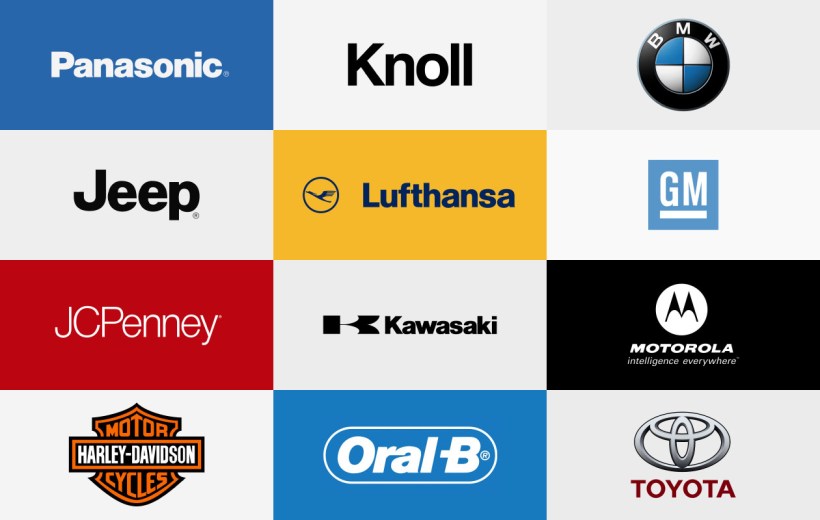
En ces jours de télétravail et de pause forcée à votre domicile en raison de l’urgence du Coronavirus, je vous propose de découvrir les documentaires du réalisateur Gary Hustwit qui a décidé de diffuser gratuitement ses films durant le confinement. Pour cette première semaine, vous pouvez voir : « Helvetica » !
Réalisé pour le 50e anniversaire de la police d’écriture Helvetica, je recommande ce documentaire qui dure un peu plus d’une heure aux amateurs de typographie. Un documentaire sur celle qui est probablement la plus connue de toutes les polices, qui est partout autour de nous, dans les publicités de Toyota, dans le logo d’Orange, dans celui d’Evian aussi… Une documentaire sur Helvetica qui nous accompagne tout le temps !
À travers ce documentaire et l’histoire d’Helvetica, on découvre une histoire du design, une vision culturelle, une histoire d’une grande importance pour comprendre l’impact des polices sur notre relation avec l’information, les marques et la communication. Le documentaire permet aussi à des designers connus de s’exprimer et illustre à quel point l’utilisation de l’écriture est omniprésente et formatrice dans notre vie quotidienne.
En bonus, quelques marques célèbres qui utilisent Helvetica :